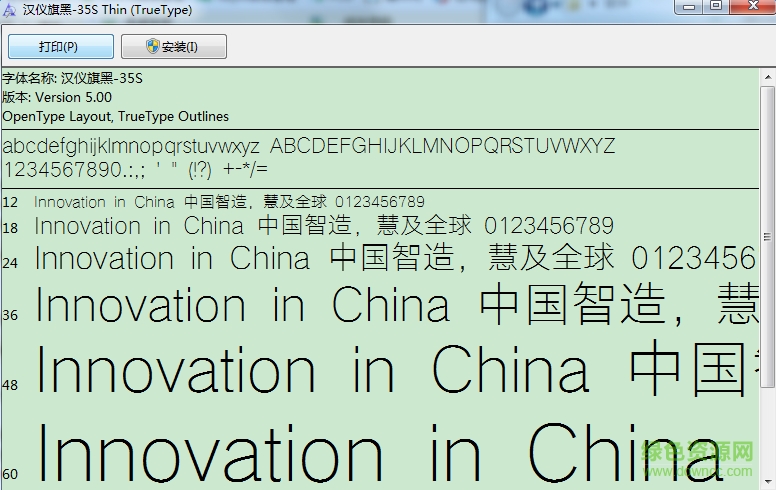
漢儀旗黑35s是一款非常經(jīng)典的漢儀字體,這款字體筆畫纖細(xì),字形端正大方,整體效果非常出色,喜歡這款字體的朋友趕緊來(lái)綠色資源網(wǎng)下載收藏吧!
此字體筆畫細(xì)膩,與時(shí)尚簡(jiǎn)體字搭配,現(xiàn)代氣息十足,整體效果比較非主流,是一款非常實(shí)用的漢儀字體。